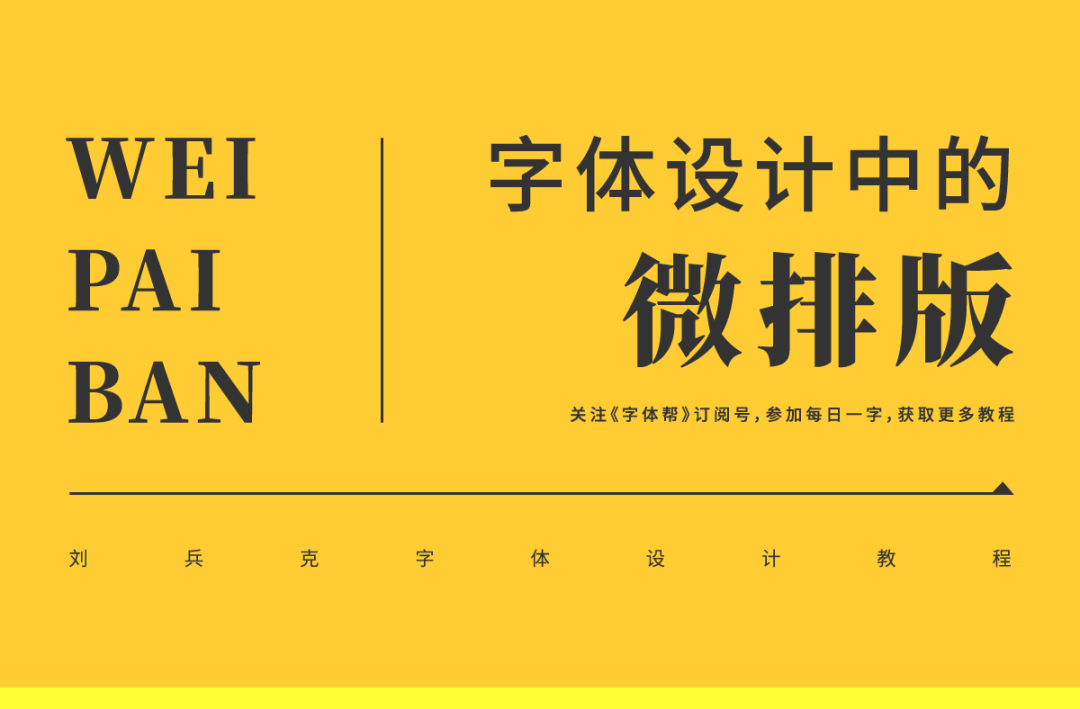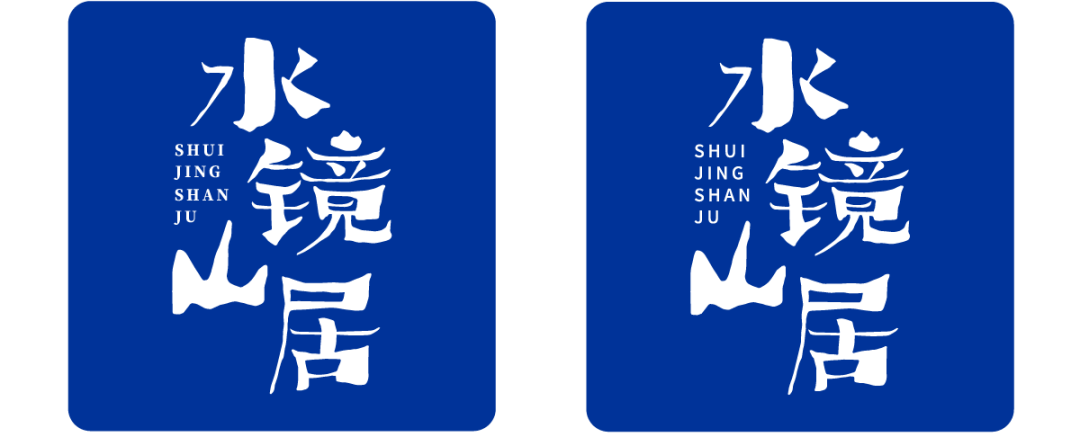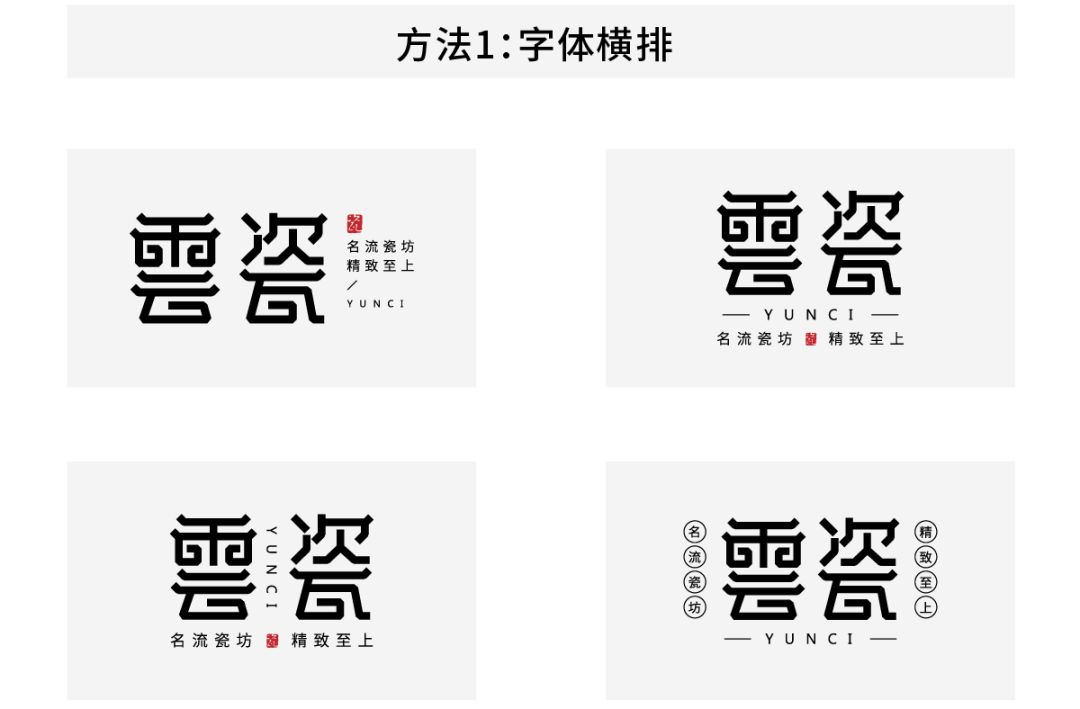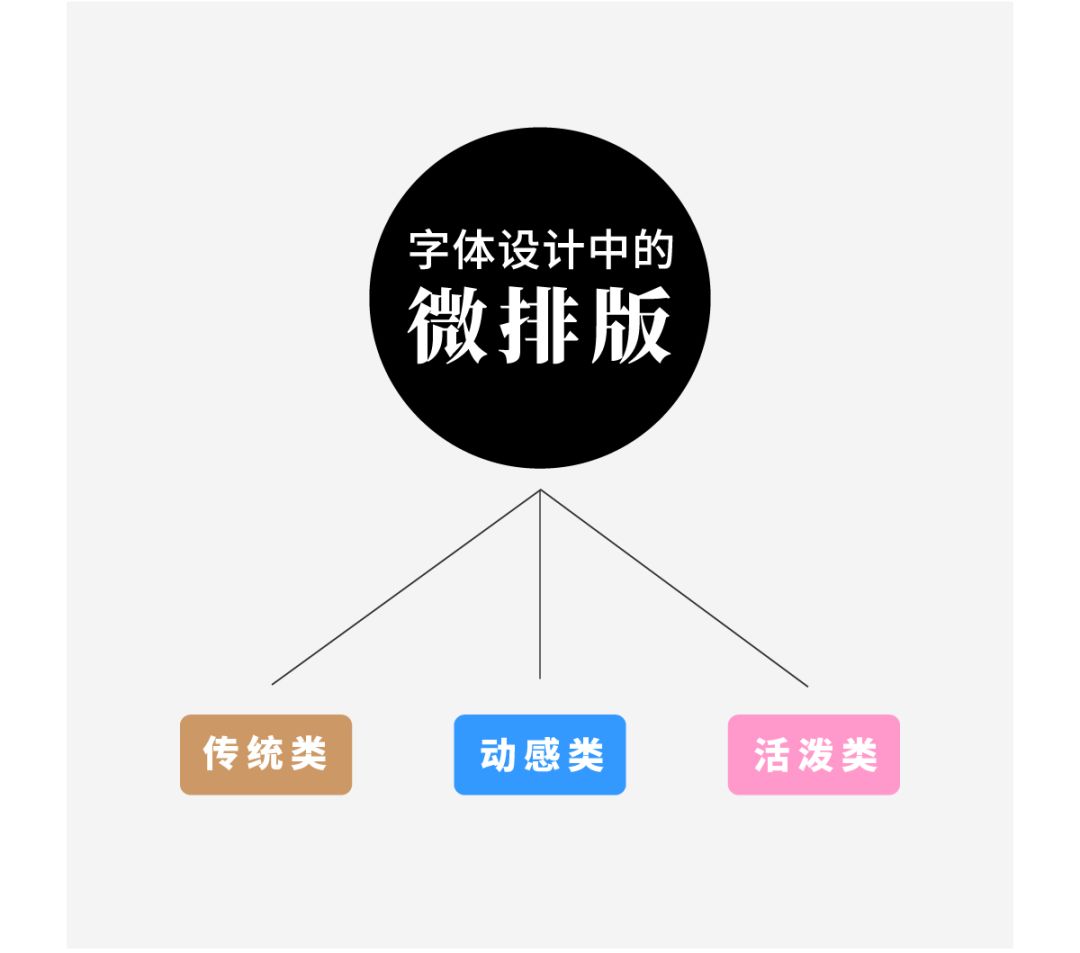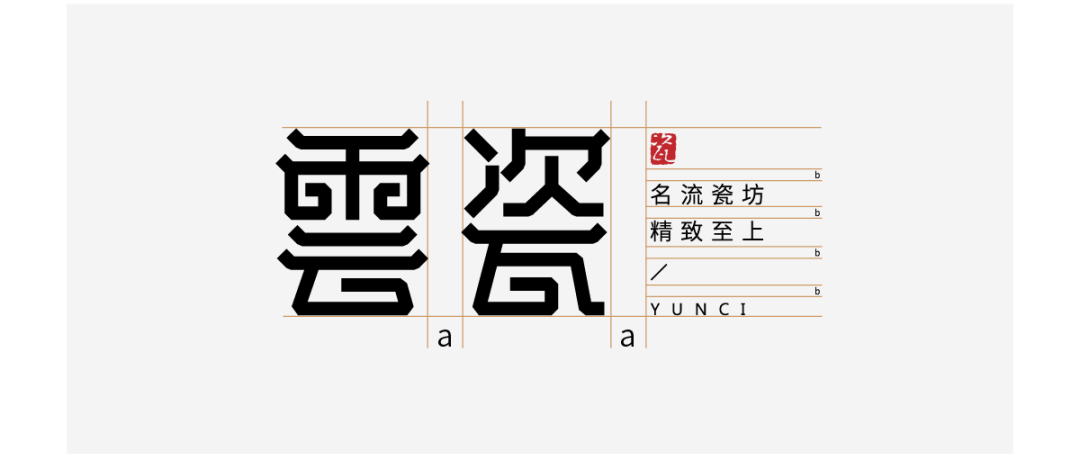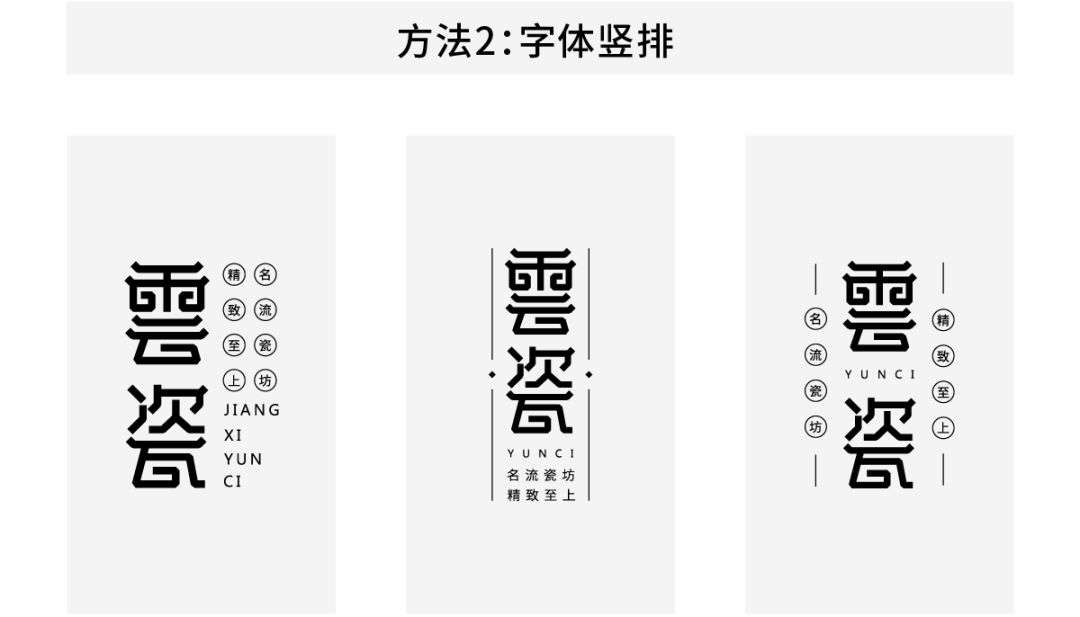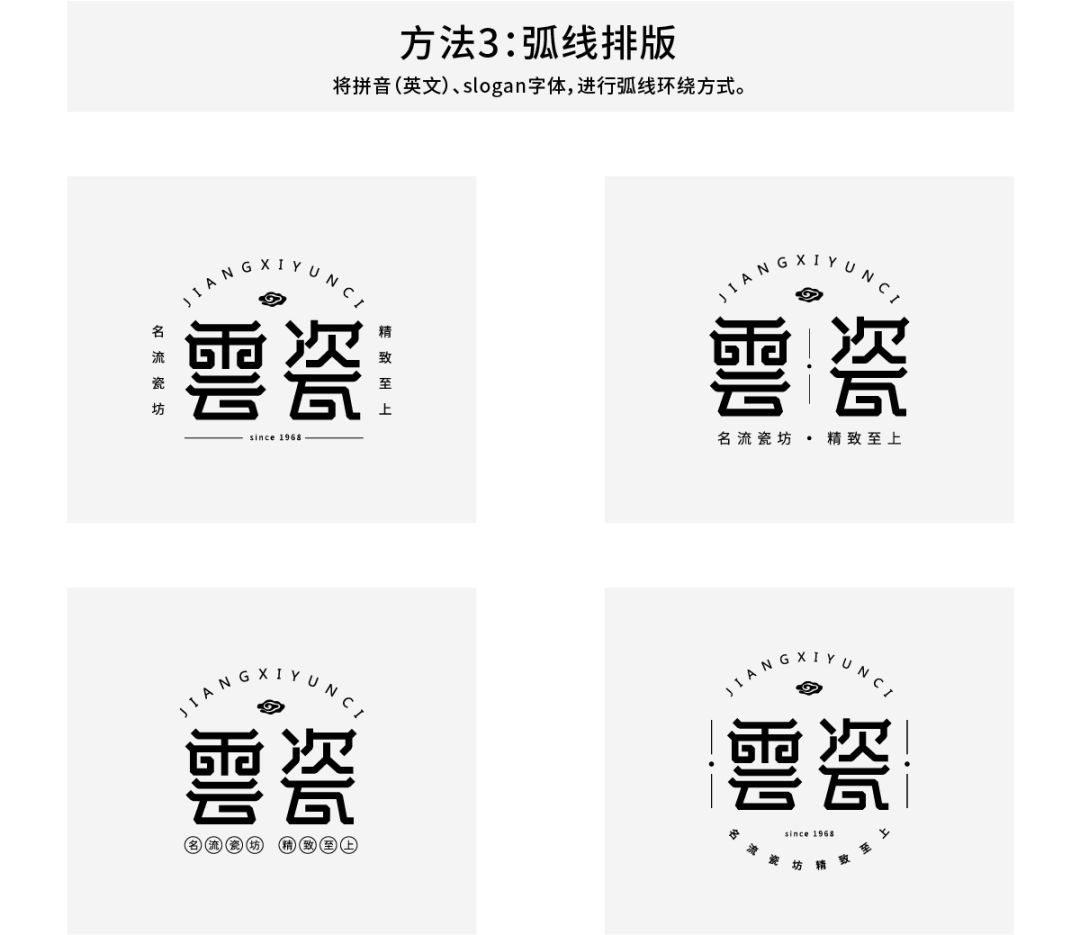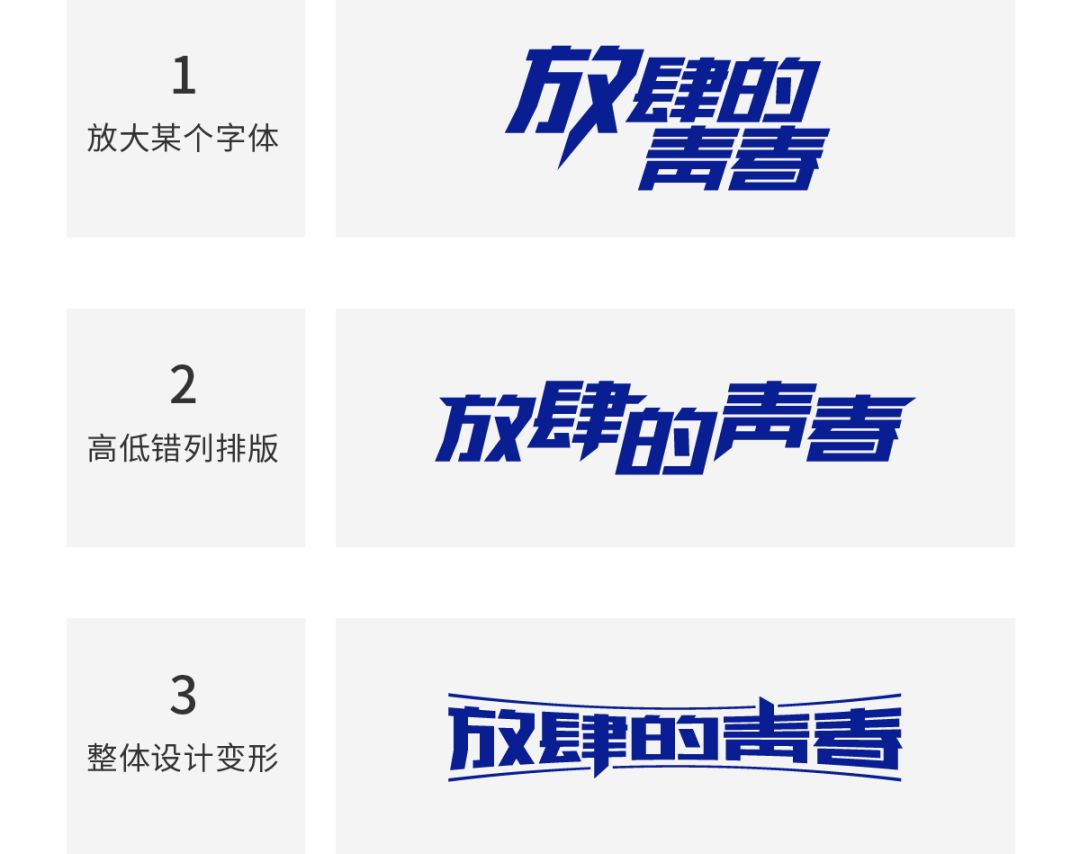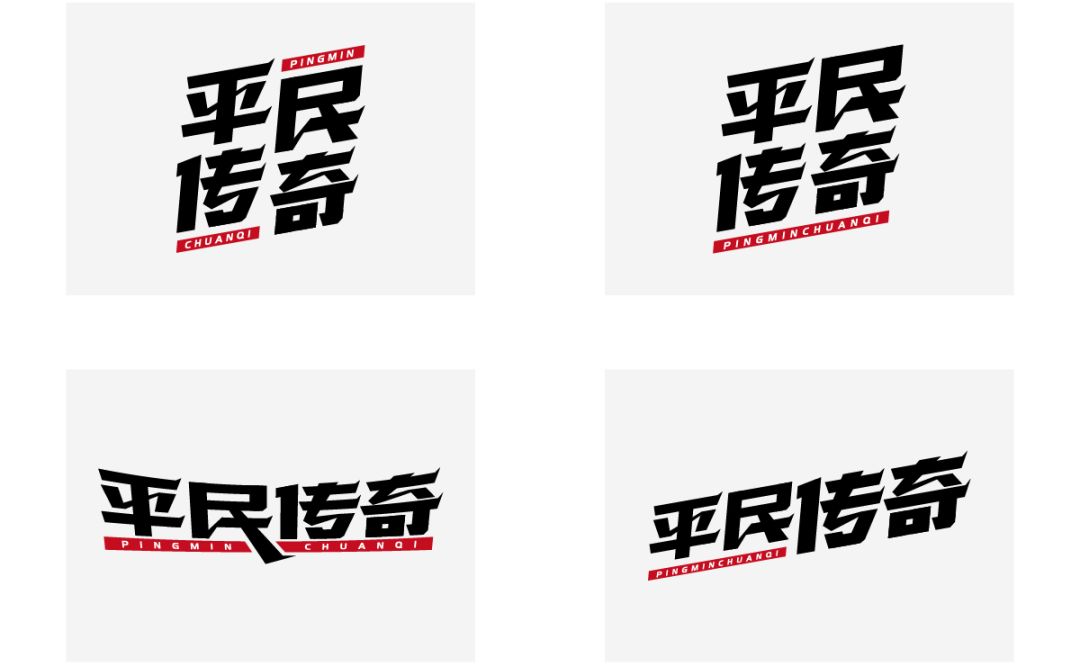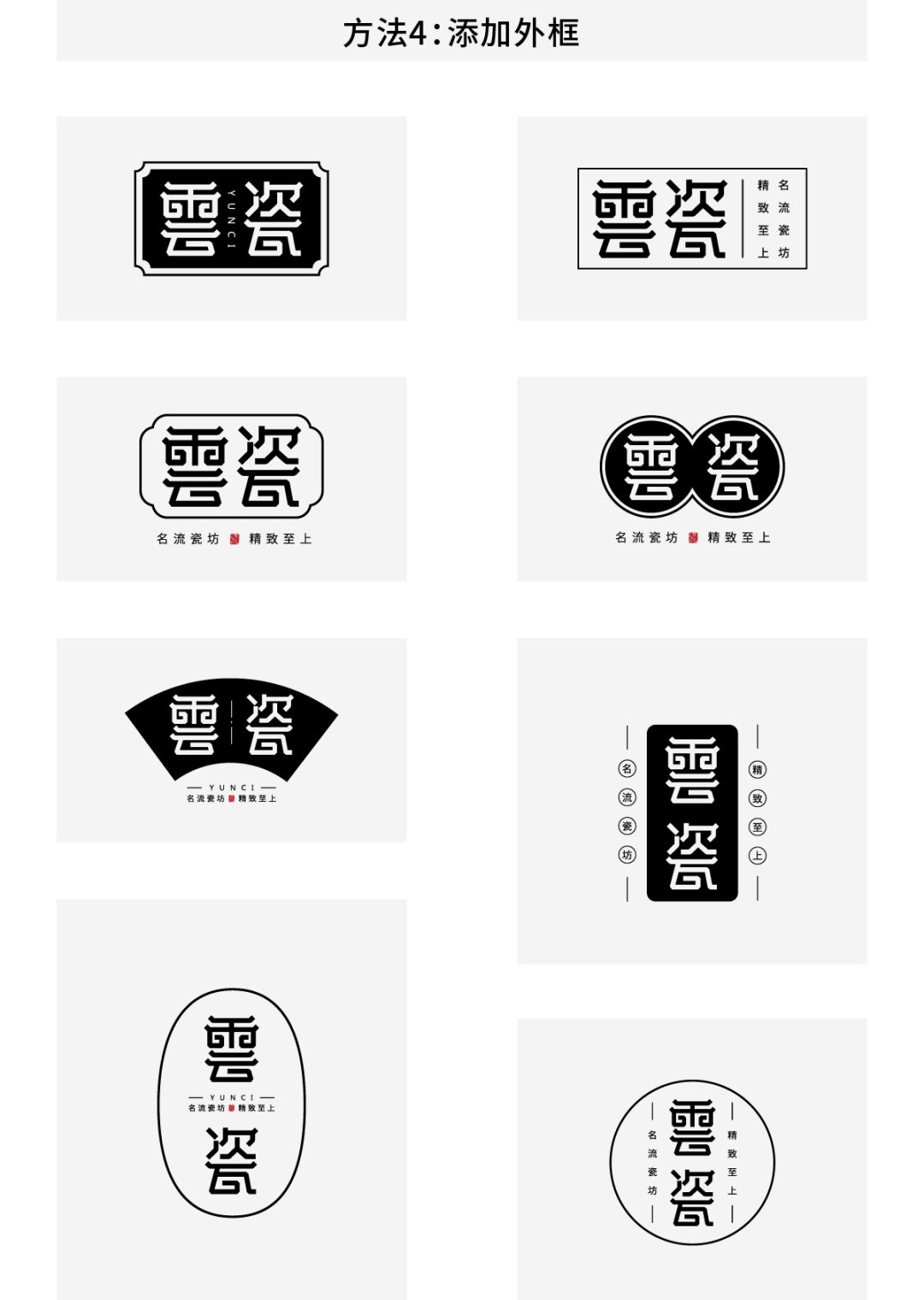
字体设计中的“微排版”,字体设计中的排版细节技巧分享
我们在设计字体时,如果只是孤零零几个字简单排列,往往会比较单调,所以,我们经常需要加入英文、标语、印章等元素进行搭配组合,这个时候,排版细节就显得至关重要了,优秀、得体的排版,可以让你的作品更加突出。
今天这篇文章,我们就来做一个总结,对字体设计中的排版细节进行大致的分析和归纳。
先说字体搭配,有很多刚接触字体设计的朋友经常忽视这个问题,在完成中文设计之后,在加入英文或拼音的时候,就随便找个字体搭进去,殊不知这种不讲究的、毫无选择的搭配,就成了整组设计的拖油瓶,你的错误搭配,就成了减分项。
所以,英文或拼音的字体选择,是绝对不能应付、不可轻视的任务,他们一定要在气质上和中文字体相近才行,只有这样,你的设计,才是协调、美观的整体。
举例如下:
1.“星粉荟”,是一家网店,售卖明星周边产品,所以中文字体,是比较时尚、潮流、个性的。而在拼音部分的字体选择上,左图,底部搭配的是衬线体,衬线体,给人的感觉是比较传统的、严肃的。这样的搭配,就好比你穿了一套时尚的衣服,却戴了一款复古的项链,格格不入,很不协调。
而右图,底部搭配的是一款非衬线体,拼音字体的端点细节,甚至也保持了“圆头”的形式,这与中文笔画,统一而协调。
这样两款字体相对比,右图,显然更合适一些,更适合这个品牌,也更符合整组中文字形的调性。
2,“水镜山居”,是一家民宿,中文设计的风格,是偏手写的感觉,在拼音的字体选择上,左图,是衬线体,右图,是非衬线体。
与第一个例子“星粉荟”恰好相反,能与中文实现最佳组合效果的,是左侧的衬线体,因为衬线体,更有历史感,更具文艺气息,在气质上,与中文“水镜山居”的氛围,更吻合一些。
除去为中文设计添加拼音、英文之外,我们也时常加入slogan、广告语等其他内容,在这些字体的选择上,方法也是类似的规律了,根据不同品牌、不同行业、不同的属性和调性,我们要仔细甄选,选择在气质上与主体字体更接近的那一款。在这里,不再赘述,不作重复。
在简单讲完如何选择字体之后,接下来,我们进入“正餐”,做更加细致、完整的总结,在这里,我用一个新词:
“微排版”
在对字体设计作品进行元素搭配时,各部分之间的排版位置,大小比例等细节,都是有章可循的,认清并把握这些规律,可以让字体作品更加耐看、更加成熟,这就是微排版的意义所在。
为了表达的更加清晰到位,我根据平时设计字体logo的经验,根据不同字形的使用频率,大致分为以下三个类别,我们从这三类字形出发,分别进行排版细节的阐述。
传统类的字体logo,很多都是工整而严谨的,一旦涉及到这类形式,我们往往需要通过调整对齐、字间距、字体大小等细节,来规范整个排版格式。
以“云瓷”为例:
左图,字体右侧部分,各元素未做对齐,空间布局不均衡,杂乱无序,而右图,在对右侧几个元素进行了左对齐之后,版面看起来更加规整、干净。
左图,“瓷”字右侧的元素,和“瓷”字间距过近,画面过于拥挤,空间被挤压,不透气。右图,间距则又过远,画面被割裂成了两部分,显得很散,所以保持适当的间距,这很重要,过近,过远,都不可取。
关于这类间距问题,可以用下面这个方法控制和检查:
在上图中,雲瓷两字的间距,以及瓷字与右侧几个元素的间距,宽度是保持一致的,距离都是“a”。而单独分析右侧几处元素,从上而下,分别是印章、slogan、斜线、拼音,这四部分,其间距也基本保持一致,距离都是“b”。
这样的间距设计,算是一个万能公式,能够最大限度的让字体logo更加工整、匀称。
另外,补充一点,我们也能很清楚的看到,印章的位置,大体与两个字顶对齐,拼音的位置,也与两个字底对齐。因为如果不做对齐处理,画面就很容易走样,比如,我们将拼音位置调高一些,看看结果如何:
在将拼音位置上调之后,通过右图示意,很明显的看到,整个设计的“矩形”轮廓被打破,右下角出现了明显空白,也就导致这例设计不够饱满,无论怎么看,都感觉“少了点东西”。
字体的大小,当然也是必须注意的事情,左图,slogan字体过小,导致阅读困难,右图,则是字体过大,抢了主体字的风头,还显得比较粗糙,不够精致。所以,这个细节,也不能忽略。
上面所列举的排版格式,是比较常见的,接下来,我们继续以“雲瓷”为例,尝试更多的排版可能性:
以上四类,是比较常见的排版方式,分别做了不同的范例展示。
但还是需要强调,所举的样例,只是抛砖引玉,是为了能够给出更多的启迪和引导,希望大家不要因此而受限。
这一类字形,是充满活力和力量的,个性张扬,意气风发。
我们可以通过字形倾斜、整体变形等方式,让字体变的更有感召力,更具设计感。
左图,是最普通的格式,没有活力,不够动感,也不够“放肆”。
而右图,这样的格式就明显好了很多,“野”了很多,首先,根据字体内容,把文字分两行排列,这样看起来会更有节奏感,接着,再进行右倾斜和上倾斜的处理,让字体往上“冲”,更有冲击力。
做完这一步之后,根据笔画情况,进行适度的夸张,在本例中,对“肆”字右下角的竖线进行了适度延长处理,这样的设计,加强了字体的个性,让字体更有张力。
接下来,根据上述理论,我们解锁更多的排版方式:
换一组案例,我们继续尝试:
平民传奇,是一档电视节目,通过词意,我们很容易提炼出“力量”、“正义”、“震撼”等此类设计关键词。那么,左图的排版形式,就比较常规,略显平淡,而在右图的设计中,先看字体细节,“民”字,最后一笔,做了延伸处理,为本身平静的字体画面,增添了动感气息,同时,这也使得字体的特征更加鲜明。而在整体上,右倾斜的方式,虽然很常见,但这样的变化,必然会让字体画面更有劲、更带感。
接下来,我们再做其他形式的排版试验:
接下来这类卡通、活泼、俏皮类的字体,与前面两类相比,在排版上的规律,相对简单一些,更容易把握。
上面两图,两例“水果忍者”,都是黑体字,左图,是普通的横排,右图,字间距拉近,每个字体都进行了角度变化,呈现“歪歪扭扭”的感觉,这样的形式,明显更活泼,更有趣。
根据这一规律,我们也可以尝试上下排列和弧度排列:
继续以“水果忍者”四字为例,我们先完成基础字的设计:
然后,我们完全按照上面的排版格式进行尝试:
在字体帮的往期作品中,有很多此类卡通字形的设计案例,我们列举几例:
这些案例的排版格式,都是轻松的、活泼的,根据不同的笔画造型,根据不同的图形创意,字体的排版也不尽相同,与“传统类”、“动感类”相比,“活泼类”的字形,因为笔画本身就比较灵活多变,所以在排版格式上,就明显自由了很多,没有那么多条条框框。
如果也将上述三类字体形式,按照人的年龄来划分,那么,“传统类”字形,是中年阶段,成熟老练;而“力量型”字形,则是青年阶段,青春焕发;“活泼类”字形,就是幼年阶段,俏皮可爱。
就像人一样,每一个年龄阶段,都要保持该有的性格才对,在对字体设计进行细节排版的时候,也必须注意字体本身的属性和性格,合适、得体的排版,会让字体作品更加出彩,而不当的排版,必然会让字体效果大打折扣。